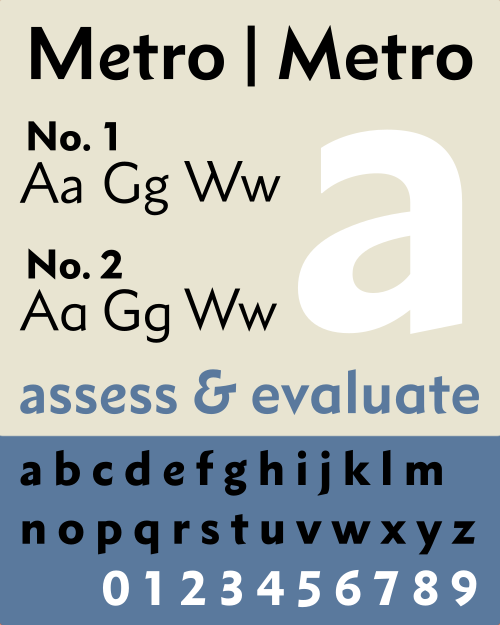
| カテゴリ | サンセリフ |
| 分類 | ヒューマニスト/幾何学 |
| デザイナー | WA ドウィギンズ |
| 鋳造所 | ライノタイプ |
| リリース日 | 1929年(メトロライト/ブラック) 1931年(メトロシン/ミディアム) 1932年(メトロNo.2) |
| バリエーション | クロニクル メトロ メトロオフィス メトロノヴァ(写真) |
| 別名 | 幾何学的 415 |
Metroは、ウィリアム・アディソン・ドウィギンズによって作成され、 1929年以降にアメリカのマーゲンターラー・ライノタイプ社によってリリースされたサンセリフ 書体ファミリーです。 [1] [2] [3]
Metro は、ドウィギンズが 20 世紀初頭の傑出したレタリング アーティストおよびブック デザイナーの 1 人として名声を確立した後、49 歳のときに作成した最初の書体です。1928 年にドウィギンズはLayout in Advertisingを執筆し、その中で「良質の」サンセリフ書体の不足を批判しました。[4]ライノタイプのタイポグラフィ担当副部長のハリー L. ゲージはこの本をレビューし、1929 年に不足していると感じた「良質の」サンセリフ書体のデザインをドウィギンズに依頼しました。コンサルタントとして迎えられたドウィギンズは、すぐに同社の書体デザイン責任者であるチャウンシー H. グリフィスと信頼関係を築きました。グリフィスは、ドウィギンズの残りのキャリアを通じて、彼の書体すべての制作を管理することになります。[5]
Metro は、フランクリン ゴシックのような伝統的な「グロテスク」なサンセリフ体ではなく、円や直線などの単純な幾何学的形状をベースとすることで注目を集めたFuturaなどの新しい「幾何学的」サンセリフ体の波に触発された。[6]これらの新しいデザインに対する彼の意見はそれほど否定的ではなかったが、ドウィギンズは既存の幾何学的書体の小文字に満足せず、純粋な幾何学から外れた、より読みやすくするフォントを作ろうと決めた。[7] [8] [9]しかし、幾何学的流行の真っ只中、彼のアプローチは期待したほど人気がなく、数年後に書体は人気の Futura に似たものになるように再設計されました。近年のいくつかのデジタル リバイバルでは、ドウィギンズのオリジナル デザインに戻ったり、代替として提供したりしています。[5] [10] [11]
背景と発展
ドウィギンズが『広告レイアウト』を執筆した頃には、マーゲンターラーのスタッフは彼が指摘した欠点を痛感していた。キーボード制御で新しい活字をソリッドブロックに鋳造するライノタイプのシステムは、手作業による植字よりもスピードが速いため新聞印刷では非常に人気があったが、高級書籍の印刷にはなかなか受け入れられなかった。1920年代までに、同社の経営陣は、このシステムの主な欠点はデザインのよいフォントが不足している点にあると感じるようになり、これを修正するために、すでに芸術顧問のエドワード・エヴェレット・バートレットを雇用していた。英国支社は高級印刷業者のジョージ・W・ジョーンズを、また競合のモノタイプ社で印刷評論家のスタンリー・モリソンを同様の理由で雇用していた。[12]
ドゥイギンズを雇ったことから、ライノタイプ社が当時流行していたヨーロッパの幾何学的サンセリフ体に対抗できる書体を求めていたことは明らかだった。ドゥイギンズは、これらの最近リリースされた書体のうち、Kabel、Futura、Gill Sansを「デザインの優れたゴシック体」とみなしたが、彼の言葉を借りれば、「大文字は良いが、小文字はひどい」ものだったという。[2]そこで彼は、純粋な幾何学にあまり依存しない書体のデザインに努め、2階建てのaとg 、かなりの幅のあるストローク幅、幅広の ペンで描いたかのようにアセンダとディセンダの末端が切り取られたものを選んだ。これらの特徴により、彼の最初のデザインはジョンストンやギル・サンズのようなヒューマニズム的な性質を帯びていたが、1932年の再デザインではよりあからさまにヒューマニズム的な要素が大幅に排除され、今日でも競合書体と同様に主に幾何学的であると考えられている。
ドウィギンズは、ファミリーの中で最も太いメトロブラックのみを描き、ライノタイプ社の製図部は彼のデザインに基づいて3つのより細いウェイトを推測した。[5]がっしりとしたデザインと広い間隔を持つメトロは、20世紀のアメリカの新聞の見出しによく使われた(多くの場合、フューチュラ、スパルタン、テンポ、ヴォーグなどの他のサンセリフ体と競合した)。また、ライノタイプ社は、低品質の新聞用紙に印刷するのに適した書体の「読みやすさグループ」の仲間としてメトロを宣伝した。[13] [7]
金属活字リリース
Metro は、Linotype のホットメタル コンポジション用に次のセットでリリースされました。
- メトロライト + メトロブラック(1929)
- メトロシン + メトロミディアム(1931)
- メトロライト No.2 + メトロブラックNo.2 (1932)
- メトロライト No.2 イタリック + ライニング メトロシン + ライニング メトロミディアム(1935)
- メトロミディアム No.2 イタリック + メトロブラックNo.2 イタリック (1937)
- メトロライト No.4 イタリック + メトロシン No.4 イタリック
最初に発売されたのはメトロライトとメトロブラックの2種類のウェイトで、後者はドウィギンズの原画に基づいて作られた。[14] [7] [15]デモとして、ロックウェル・ケントの『荒野:アラスカの静かな冒険日誌』がメトロライトで印刷された。[5] 1931年にはメトロシンとメトロミディアムという2種類のウェイトが追加された。
Linotype システムは文字構造に制限を課し、同じ「二重」マトリックス上に 2 つのフォントを提供するのが標準でした。したがって、同じ幅である必要がありました。そのため、Linotype は Metrolite と Metroblack をペアで提供し、続いて Metrothin と Metromedium を提供しました。互いに大きく異なる太さの間でメトリックを共有することを余儀なくされた結果、太さが増すにつれて、グリフの形状はより幅広とより凝縮された状態の間を行ったり来たりします。
Metroシリーズは生産開始後に再設計され、当時人気だったドイツのバウアー活字鋳造所のFuturaファミリーを模倣するためにいくつかの文字が変更された。 [16] [17]小文字のaとgは1階建てになり、湾曲したeは水平バーを備えたより一般的なバージョンに置き換えられ(元々は代替として提供されていた)、大文字のA、M、V、Wは尖った頂点が付けられるなど、他の変更も行われた。新しいファミリーは「Metro No. 2」と名付けられ、交換用のNo. 2マトリックスを交換することで形成できるようになった。[5] Linotypeは、 Kabel風の4つの尖ったWと角度のついた横棒を備えたe 、装飾的なStreamline Moderneスタイルの「Unique Capitals」など、他の代替もいくつか提供した。[5]
イタリック体は主に斜体で、後から追加されたもので、異なるウェイト間で一貫性がありません。メトロシンイタリック体だけがfに下垂体があり、Futura のようにまっすぐなt があります。小文字のイタリック体のfとt は他のウェイトではより顕著な曲線を描いていますが、小文字のj は不思議なことに曲線がありません。これらの特徴はデジタル版にはほとんど引き継がれておらず、一般的に単純な斜体が採用されています (下記参照)。[5]
デジタルによる復活と解釈
Linotype とその所有者でありかつてのライバルであるMonotypeによって、いくつかのデジタル化がリリースされています。
- 最も初期のデジタルメトロであるメトロNo.2は、金属活字での使用に基づいています。メトロライト、メトロミディアム、メトロブラック(メトロシンはデジタル化されていない)の3つのウェイトがあり、イタリック体はありません。[5]各ウェイトには2つのバージョンがあります。1つは基本的なラテン文字セットで、もう1つはアクセント付きおよび特殊なラテン文字のより完全なコレクションです。[18]
- 小林明がデザインし、2006年に発売されたメトロオフィスは、ドウィギンズのオリジナル文字(丸みを帯びた小文字のeを除く)を一部使用した現代的なデザインとなっている。その名前が示すように、このフォントはワープロアプリケーション向けに設計されており、2つのウェイトと斜体を備えている。4つのスタイルはすべて、互いにだけでなく、Linotypeの「オフィス」シリーズの他のすべてのメンバーともメトリックを共有しているため、テキストのリフローなしでフォントとスタイルをシームレスに変更できる。ただし、これは多くの文字の形状が変更されたことも意味しており、オリジナルと比較して「より緩やかで、より伝統的な美観を与えている」。[5]イタリック体には、メタルバージョンのメトロシン(他のウェイトにはない)の特徴であるディセンダー付きの小文字のf も含まれている。[19]
- 2012年にLinotype: The Filmのために大曲俊一がデザインし、2013年に商業的にリリースされたMetro Novaは、Dwigginsのオリジナル図面に戻りつつ、アクセント付きおよび代替グリフの完全な範囲で文字セットを拡張しています。Metro No. 2の文字は、テキスト数字とスモールキャップスとともに、OpenTypeスタイルセットで提供されています。ウェイトの範囲は7つに拡張され、6つのコンデンスウェイト(すべて斜体)が追加されました。ウェイトの命名もオリジナルのMetroに対応しておらず、オリジナルの4つのウェイトは、Metro NovaではおおよそLight、Regular、Medium、Blackに相当します。拡張されたオプションの範囲を作成するにあたり、デザインはオリジナル(Linotypeマシンでウェイトを二重化するため、文字幅が広い形と狭い形を行ったり来たりしていた)と比較して規則的になり、金属製のバージョンと比較して独特の特徴を備えています。[5]それにもかかわらず、これは市場に出回っているバージョンの中では群を抜いて最も完成度が高く、ドウィギンズのオリジナルデザインに最も近いものです。[20] [5]
公式の Linotype デジタル化の他に、Metro をベースにした非公式の復活版やデザインが数多く登場しています。
- ビットストリームは1990年にメトロをジオメトリック415としてデジタル化した。このバージョンは3つのウェイト(ライト、ミディアム、ブラック)と斜体、そして基本的なラテン文字セットを提供している。ティルデもこのデザインのバージョンで、より幅広いアクセント付きラテン文字を提供している。このバージョンのフォントは、デジタル製品の中で唯一、メタルバージョンの特徴的な小文字のfとtのグリフを保持した斜体を含んでいる。[21]
- GroupType のDetroit Metro はGrosse Pointe MetroまたはDH Sansとしても知られ、金属製の Metro No. 2 をほぼそのままベースにしたバージョンです。「DH Sans」と「Grosse Point Metro」のバージョンには直立形から派生した斜体が含まれていますが、「Detroit Metro」には「ソフト」(丸みを帯びた) バージョンと、輪郭が不完全に塗りつぶされた 2 つの「ラフ」バージョンも含まれています。[22] [23] [24]
- 1930 年初頭のメトロブラックの広告
- 1930年の広告
- 1932 年の広告。「メトロ 2 号」の新しい代替文字を表示